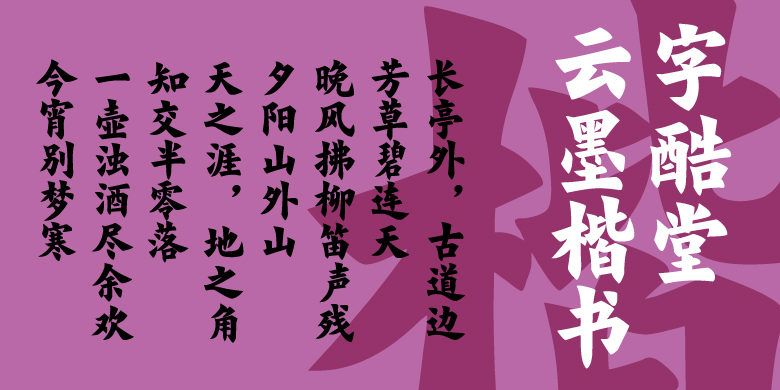
字酷堂云墨楷书
楷书、常规书写·毛笔
字酷堂云墨楷书,字体风格源于欧楷名家王维贤,同时为符合当代审美需求,对笔画与结构做了适当调整。字体笔画线条挺拔有力,字形厚重工整,宽博大气,具有“温文尔雅”的文人之气。 王维贤,清末民初天津著名书法家,以欧楷造诣闻名。其书法深得欧阳询精髓,笔法以方笔为主,起笔处多见切面,转折利落,线条厚重而不失灵动。在结体上,他既保留了欧楷险绝挺劲的特点,又融入小楷、颜楷及魏碑笔意,形成端庄大气、法度严谨的风格。代表作《临化度寺碑》笔力凝聚,字形随势赋形,横画纤细而竖画粗重,强化了视觉对比。王维贤的书法不仅重现了唐楷风骨,更推动了欧楷在近代的传承发展,堪称融古出新的典范。